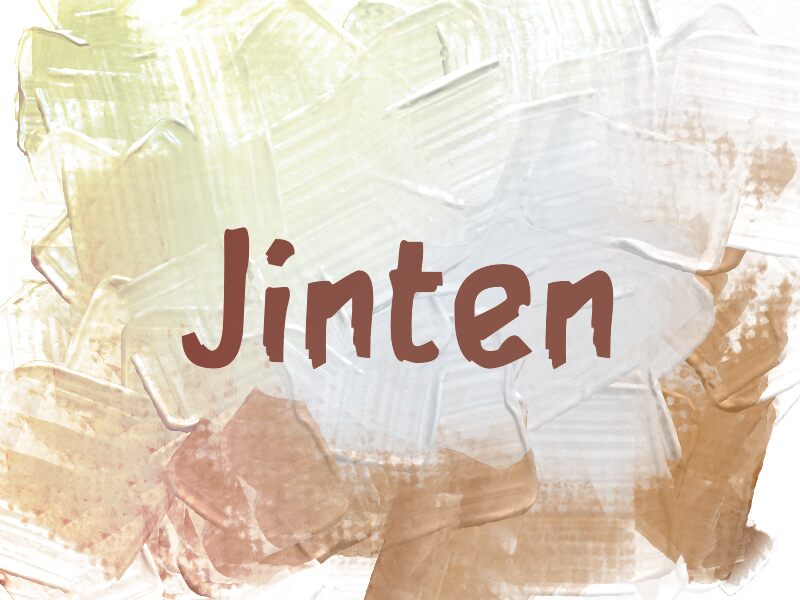
Jinten
Jinten от Wep — это бесплатный рисованный шрифт, который отлично подходит для постеров благодаря своему непринужденному, броскому характеру. Буквы выглядят так, словно их вывели кистью, щедро набрав на неё краску: плотные штрихи, тупые окончания и слегка неровный ритм придают им непосредственный, «живой» вид.
Этот шрифт идеально впишется в дизайн упаковки продуктов, оформление кафе, афиши мероприятий, графику для соцсетей и короткие заголовки, где рукописный стиль важнее отполированной точности. Будучи бесплатным, Jinten также отлично подходит для титульных карточек и быстрых набросков логотипов: мощные формы мазков кисти делают даже простые слова выразительными и «человечными».